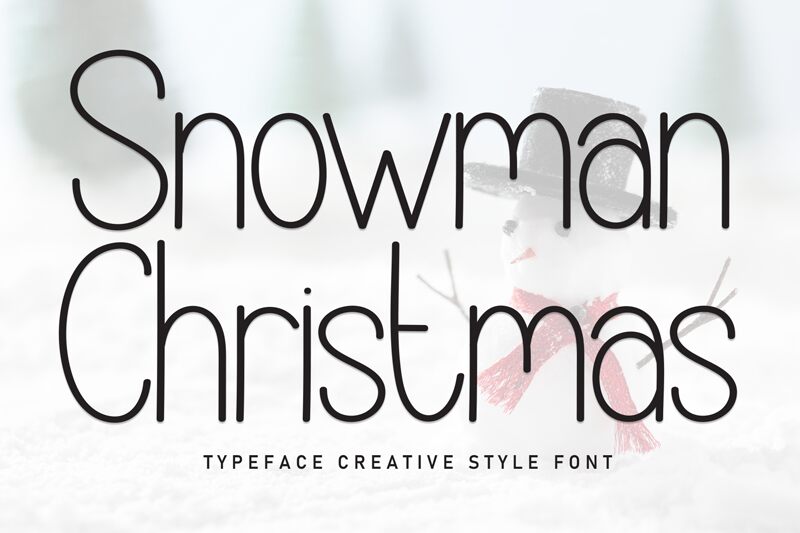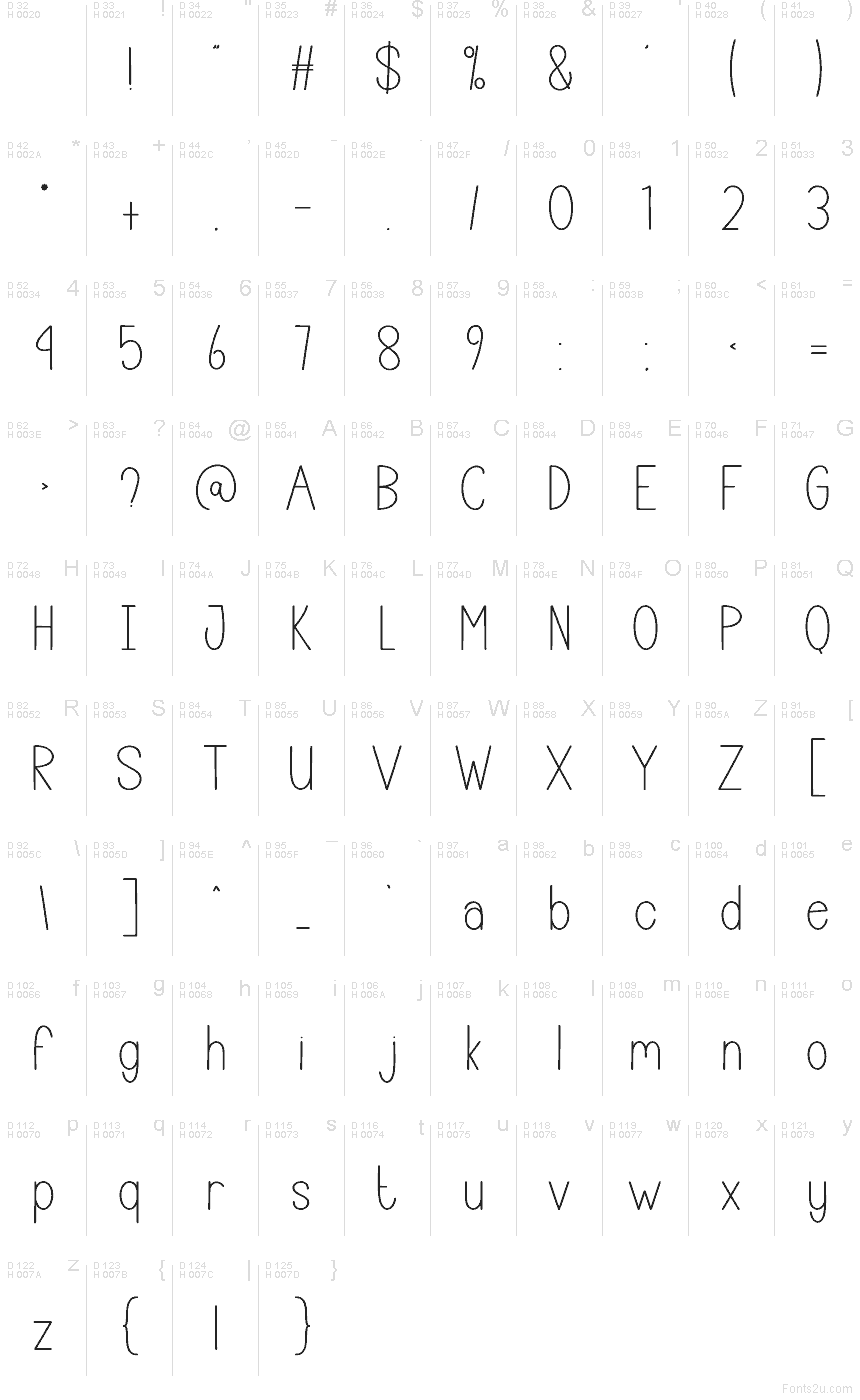
Snowman Christmas est une police manuscrite monoline gratuite, au rythme léger et aérien, parfaite pour vos créations de fin d'année. Les lettres semblent tracées d'un seul geste fluide, mélangeant des formes hautes et étroites avec des courbes larges et ouvertes pour un rendu simple, convivial et légèrement fantaisiste.
Idéale pour le branding saisonnier, les étiquettes cadeaux, les cartes de vœux, les invitations ou les packagings où une écriture trop classique serait trop chargée. En tant que police gratuite, elle est également parfaite pour les posts réseaux sociaux, les titres de couverture et les cartes d'en-tête, car son tracé épuré donne à vos textes un aspect décontracté tout en restant personnel.
Présentation et spécimen de la police Snowman Christmas
Table des caractères de la police Snowman Christmas
Table des caractères de Snowman Christmas : Latin de base, page 1
Glyphes de la police Snowman Christmas — Latin de base, page 1
Snowman Christmas